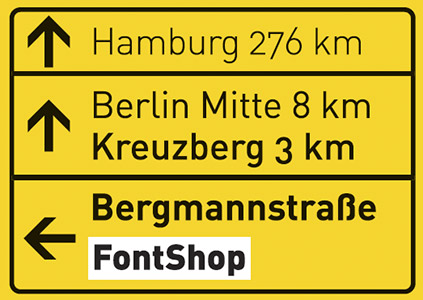
Sammelkarte: DIN-Schrift mit AnspruchIm Juli 1995 erschien eine Überarbeitung der berühmten
DIN-Schrift, auf die viele Gestalterinnen und Gestalter gewartet haben: die FF
DIN. Endlich ausreichend Strichstärken, ein Standard-Zeichenvorrat und
sogar alternative Zeichen mit runden Punkten und offeneren Formen. Binnen
![]() Die FF DIN von Albert-Jan Pool ist nicht am
Reißbrett entstanden. Pool ist ein erfahrener Schriftentwerfer, der
weiß, dass vermeintlich konstruierte Schriften einen Hauch Kontrast
aufweisen – wenn sie gut gemacht sind . Schon aus diesem Grund musste er
die DIN-Schrift völlig neu zeichnen. Dabei legte er den Grundstein so, dass
er 5 Strichstärken entwickeln konnte. Zusammen mit den Alternativ-Schnitten
ergaben sich bei der Premiere der FF DIN 10 Fonts, mit denen man endlich
hochwertige Typografie betreiben konnte.